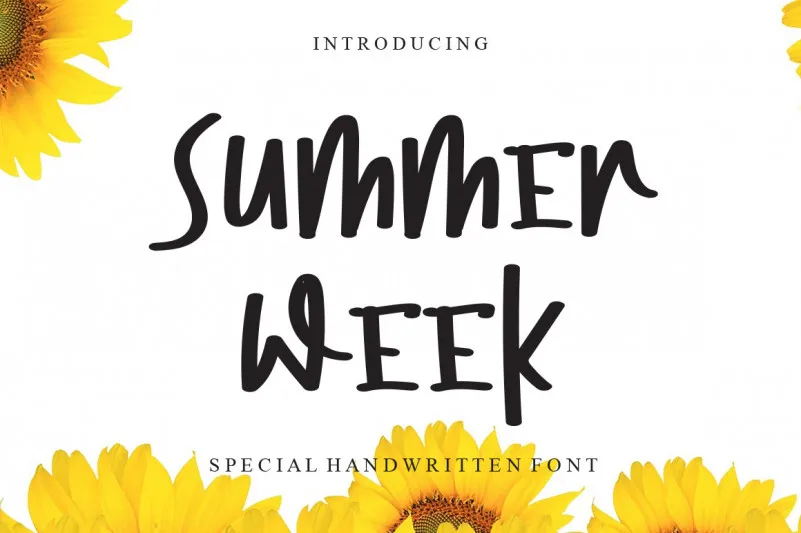
Summer Week Font – Download Grátis
A Summer Week Font é uma escolha perfeita para quem busca uma fonte escrita à mão com personalidade. Ela se destaca por sua leveza e originalidade, tornando-a ideal não apenas para criações infantis ou relacionadas a quadrinhos, mas também para qualquer projeto que busque um toque de beleza sofisticada. Compreendendo o poder da escrita à mão em transmitir sentimentos e conceitos, esta fonte é uma excelente opção para designers buscando expressar ideias criativas em cartazes, capas de livros ou até mesmo textos informativos. Suave e encantadora, ela se adequa perfeitamente a diferentes tamanhos e contextos gráficos, tornando-a uma opção versátil que pode ser usada em diversos projetos. Seja você um designer de jogos infantis ou criador de conteúdo digital, a Summer Week Font é uma excelente escolha para aqueles buscando algo mais do que apenas uma fonte. Com sua personalidade encantadora e originalidade, ela irá adicionar um toque único e agradável a qualquer projeto.